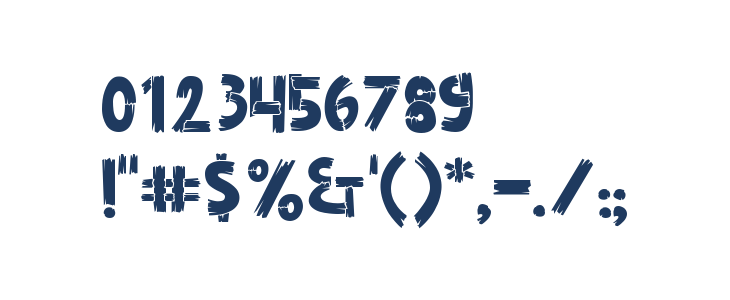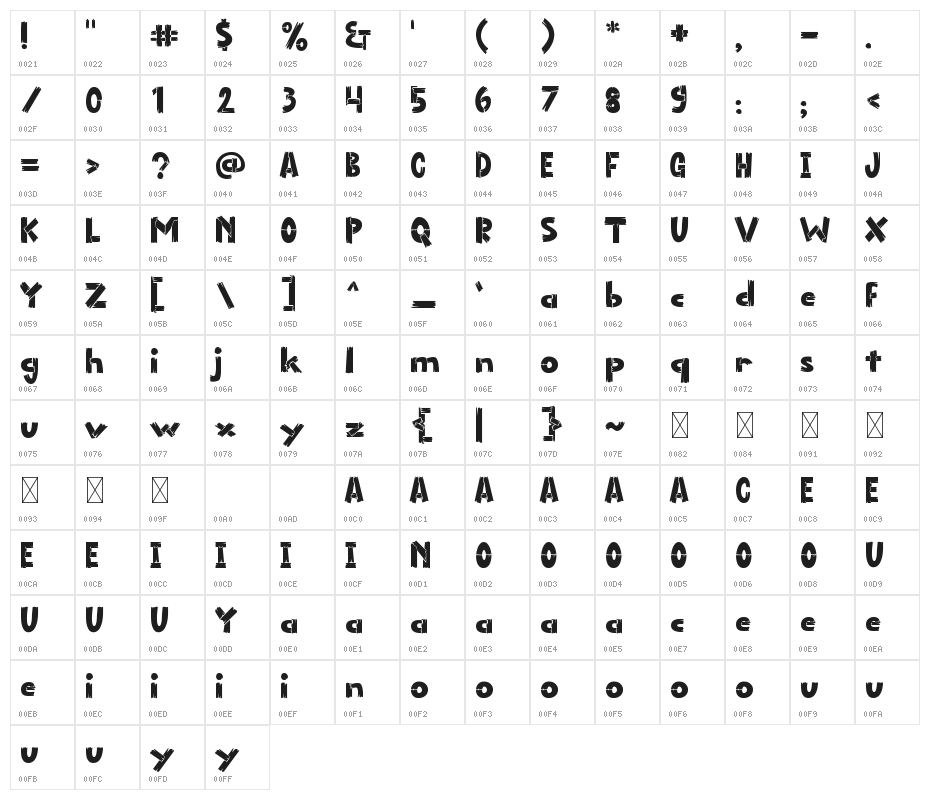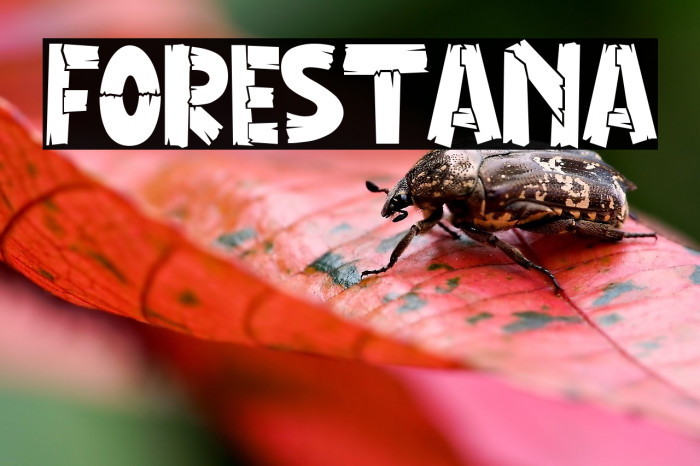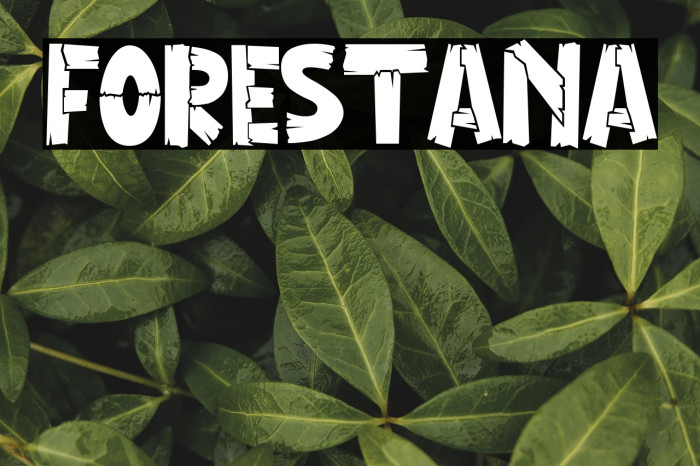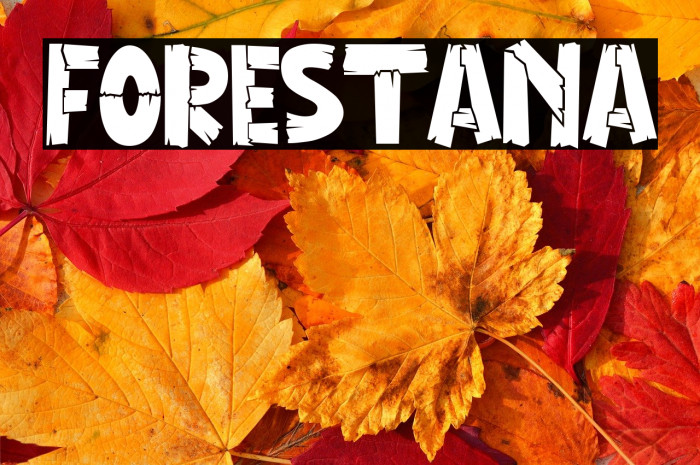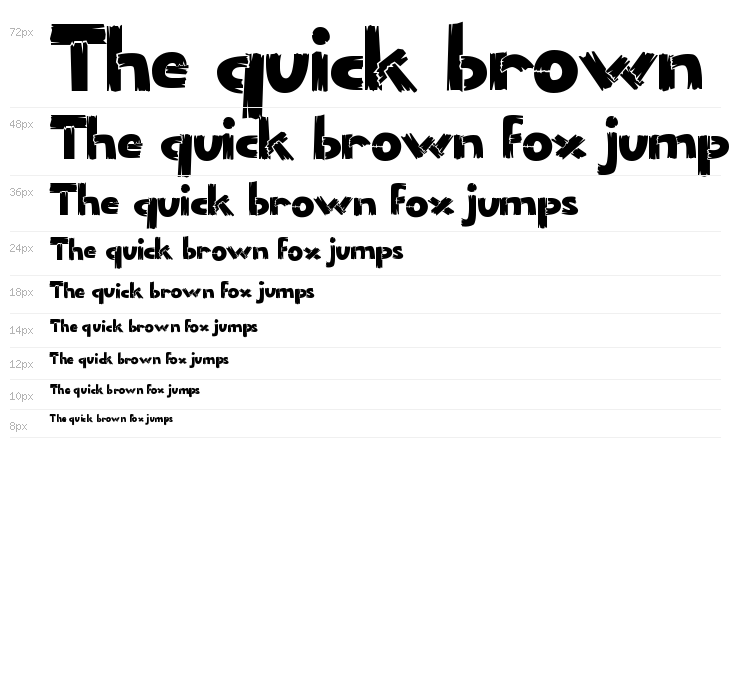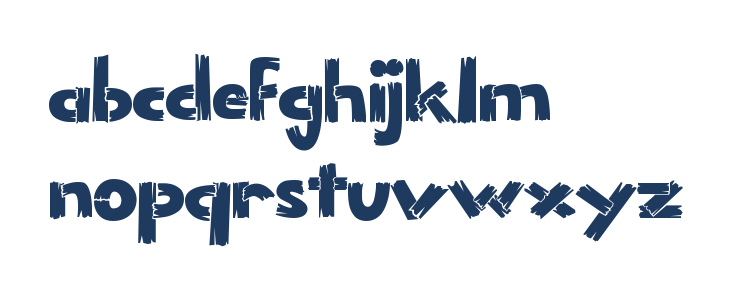
FORESTANA Font
✎ Decorative
| Vorgeschlagene Projekte | Ideal for nature-themed posters, outdoor event flyers, eco-friendly product packaging, and adventurous branding projects. |